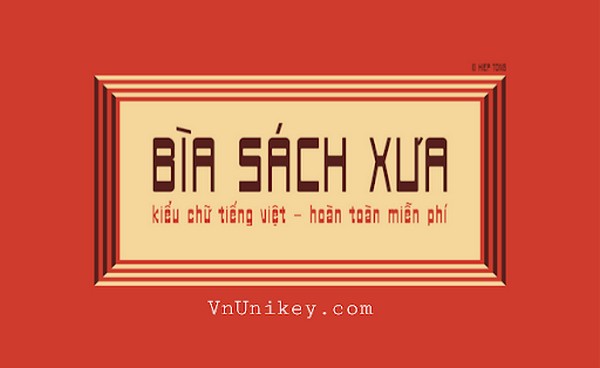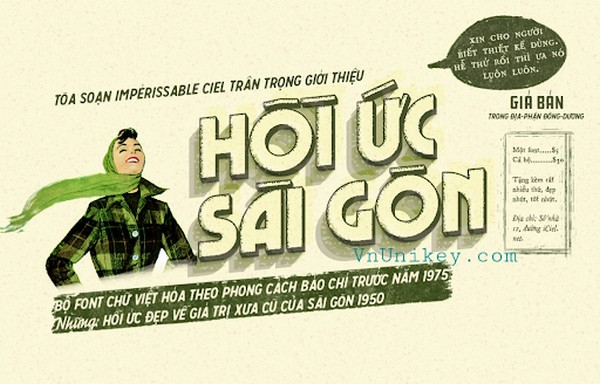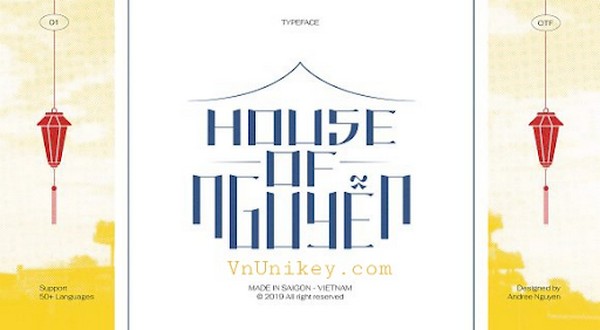
Nếu bạn muốn thiết kế những tấm áp phích hoặc pa-nô theo phong cách xưa cũ đặc trưng của người dân Việt thế kỷ trước thì không nên bỏ qua font chữ bảng hiệu xưa? Vậy font chữ bảng hiệu xưa là gì? Có những font chữ bảng hiệu xưa nào đẹp, thu hút người nhìn? Cùng chúng tôi tìm hiểu qua bài viết dưới đây nhé!
Font chữ bảng hiệu xưa là gì?
Font chữ bảng hiệu xưa là một diễn đàn font chữ được sử dụng khá phổ biến bởi cộng đồng thiết kế người Việt. Những hội nhóm chuyên để thảo luận về đồ họa. Tại đây học sẽ có nhóm chuyên phụ trách việt hóa những font chữ đang hot, các mẫu thiết kế phải kể đến đó chính là myfonts, Typography.com,…và chia sẻ chúng miễn phí cho những người có mong muốn sử dụng. Trong đó nổi bật nhất đó là font chữ thời bao cấp, font chữ xưa và font chữ bao cấp.
Top 8 font chữ bảng hiệu xưa đẹp nhất
Font chữ hồi ức Sài Gòn
Bộ font chữ này gồm 32 font chữ Việt hóa, được tác giả chọn lọc kỹ lưỡng sau khi kỳ công tìm kiếm các tư liệu, hình ảnh về Sài Gòn trước năm 1975. Mỗi một font chữ đều được tác giả trau chuốt một cách kỹ càng kể cả những con dấu nhằm mô phỏng hoàn toàn chữ viết được in trên mặt báo chí, mẫu quảng cáo hay các bảng hiệu Sài Gòn trước năm 1975.
Font chữ giá trị xưa cũ
Bộ font chữ giá trị xưa cũ được thiết kế dựa trên nguồn cảm hứng từ những bảng hiệu vẽ tay từ thời bao cấp. Tác giác đã chọn lọc kỹ lưỡng, Việt hóa theo phong cách bỏ dấu xưa, rất phù hợp với những tấm poster, bảng biển quảng cáo đậm chất hoài cổ. Font chữ giá trị xưa cũ độc quyền của bảng hiệu xưa được thiết kế trong gần 2 tháng, kể từ khi nghiên cứu cách bỏ dấu cho tới việc chăm chút từng đường nét.
Font chữ hòn ngọc viễn đông
Hòn ngọc viễn đông cũng là một trong những sản phẩm kỳ công đến từ font chữ bảng hiệu xưa. Font chữ mang phong cách xưa cũ, dựa trên ý tưởng gọi nhớ về các bảng hiệu Sài Gòn xưa, logo từ thế kỷ 19, thời điểm mà Sài Gòn được ví giống như Hòn Ngọc Viễn Đông của châu Á.
Tác giả phải nghiên cứu hàng trăm bức ảnh bảng hiệu Sài Gòn khác nhau để rồi chỉnh sửa, thiết kế sao cho đẹp mắt nhất có thể nhưng vẫn phải giữ được cái hồn của kiểu chữ xưa cũ. Font chữ này chắc chắn sẽ có thể làm hài lòng những người thiết kế khó tính nhất.
Font chữ Classique Saigon
Classique Saigon là một trong những font chữ được thực hiện bởi Manh Nguyen, một nhà thiết kế theo đuổi lĩnh vực sáng tác font chữ ở Hà Nội.
Font chữ Classique Saigon được bắt nguồn từ bộ phim đình đám như Cô Ba Sài Gòn đã trở thành hiện tượng và khơi gợi nguồn cảm hứng cho những người thích hoài niệm, đặc biệt là những người yêu mến kiểu chữ của các biển hiệu Sài Gòn thập kỷ 50-60 thế kỷ trước. Một Sài Gòn hoa lệ nhưng mang đậm chất thôn quê Việt bỗng hồi sinh. Từ màu sắc, hình ảnh cho đến thiết kế font chữ Classique Saigon đều thể hiện được sự công phu, góp phần truyền bá và hồi sinh văn hóa Sài Gòn cũ đến với công chúng.
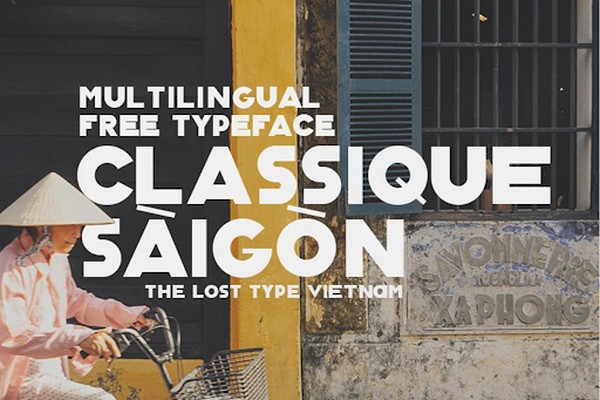
Font chữ xưa cũ
Bộ font xưa cũ bao gồm 67 font theo nhiều phong cách bảng hiệu thời xưa của Việt Nam do anh Lê Tuấn Anh sưu tập thời gian gần đây.
Font chữ bìa sách xưa
Nếu bạn yêu thích những nét chữ được ghi trên các tấm banner quảng cáo hay bìa sách lâu đời của người Việt từ những năm 1980 thì không nên bỏ qua font chữ này.
Font chữ bìa sách xưa được tạo ra và phát hành bởi ông Tống văn Hiệp. Ý tưởng của font chữ này chính là từ những cuốn sách cũ, kiểu chữ có đường ngang dày và nét thẳng thì thanh mảnh.
Font chữ lạc tự
Đây là bộ font chữ được tạo ra bởi Mark Trinh. Sản phẩm được lấy cảm hứng từ những biển quảng cáo tại các thành phố lớn của Việt Nam thập niên 80, 90. Và tập trung chủ yếu vào 2 thành phố lớn đó là Hà Nội và Sài Gòn. Vì 2 thành phố này là trung tâm văn hóa, kinh tế, chính trị lớn nhất của đất nước.
Font chữ House of Nguyen
Đây là bộ font chữ của tác giả Nguyễn Minh Tuấn, ông đã dày công nghiên cứu và thiết kế. Ông mong muốn mang đến bộ chữ ký latin quốc ngữ, nhưng mang hơi hướng của phong cách kiểu Hán. Sản phẩm tái hiện sự giao thoa văn hóa giữa phương Tây và châu Á ngay tại nước mình, khi người Pháp vào mang theo chữ quốc ngữ, trong khi chữ Nho, chữ Nôm vẫn còn tồn tại.